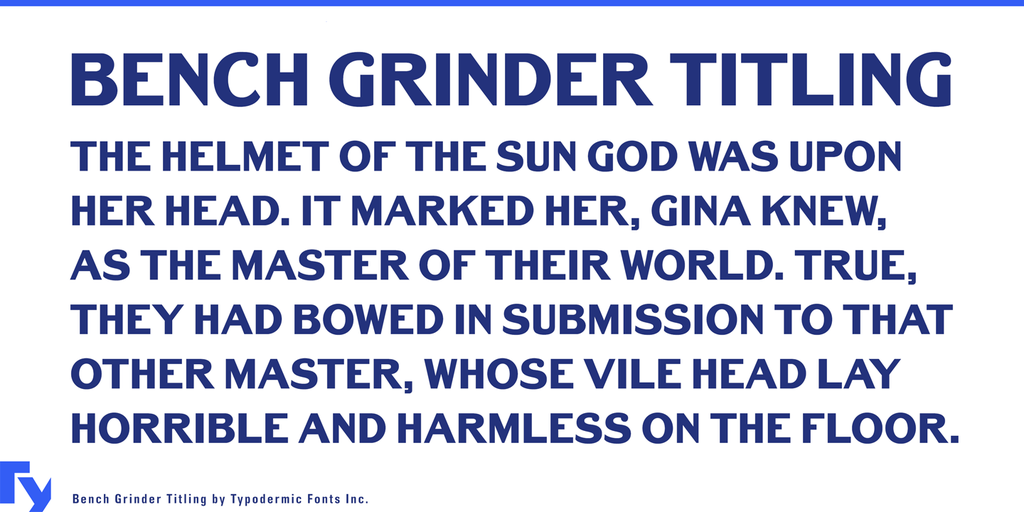
A Bench Grinder Titling Font é uma criação inspirada nos traços das fontes de headlines do século XIX feitas à mão no metal, mas sem as serifas slabs característicos dos typodermicfonts.com. Seu design não segue o padrão convencional da tipografia, oferecendo um resultado único e desafiadoramente atraente para utilização em títulos de texto. Com uma sensação familiar que se mistura com uma dose generosa de originalidade, essa fonte é perfeita para quem busca algo singular no meio das grandes variedades disponíveis atualmente. Para aqueles que buscam um match completo, há também a opção do versão regular da Bench Grinder para títulos em minúsculas. Estas características tornam a Bench Grinder Titling Font uma escolha inteligente para designers buscando adicionar um toque único e memorável ao seu trabalho visual.